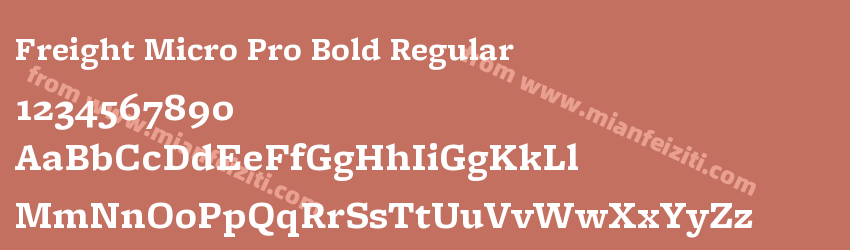
Freight Micro Pro Bold Regular
字体名称: Freight Micro Pro Bold Regular
字体字重: FreightMicro Pro Bold
本款“Freight Micro Pro Bold Regular”是一款书写很新颖的字体,字体大方,适合各种设计作品使用!欢迎下载!